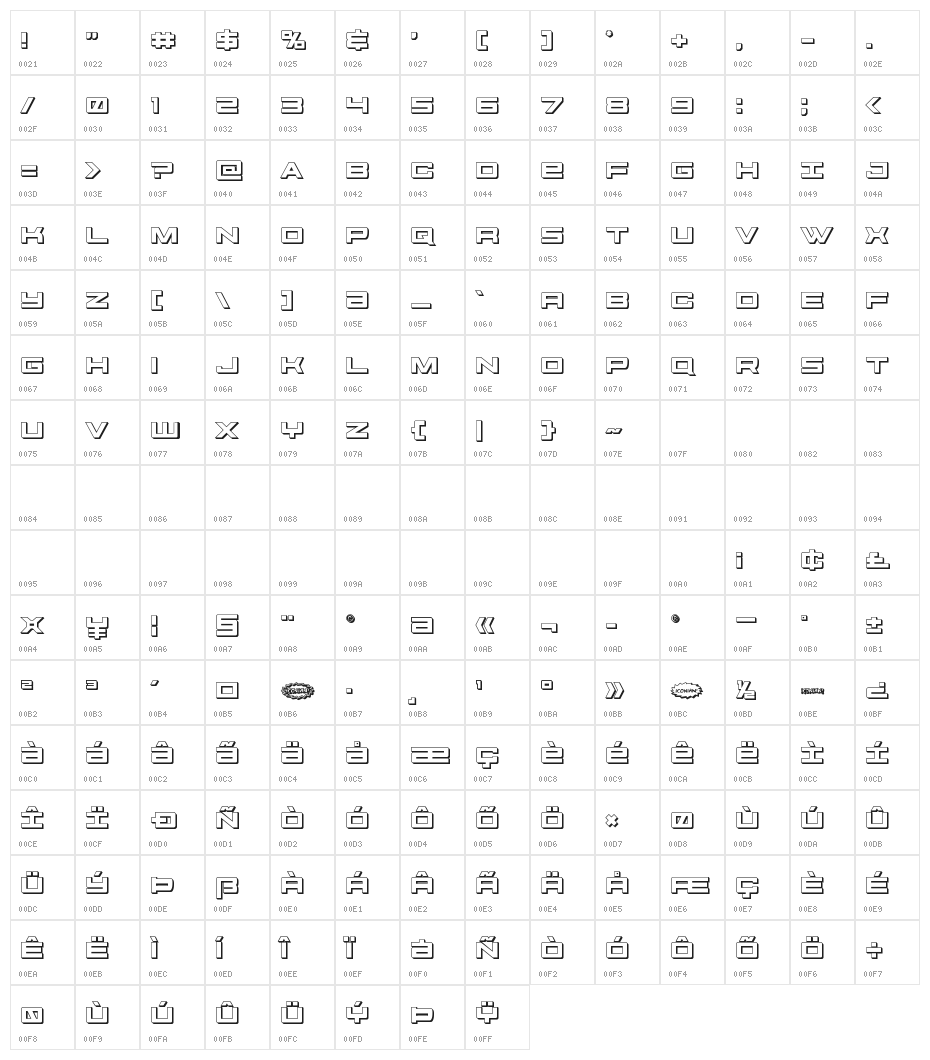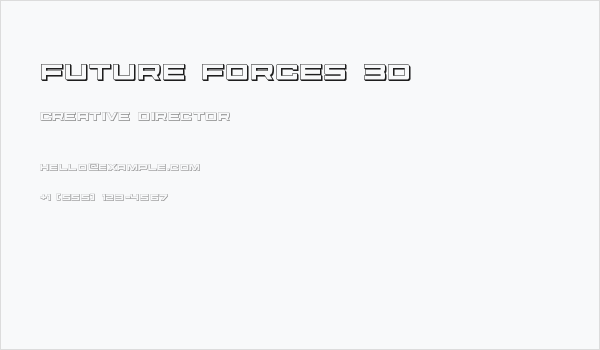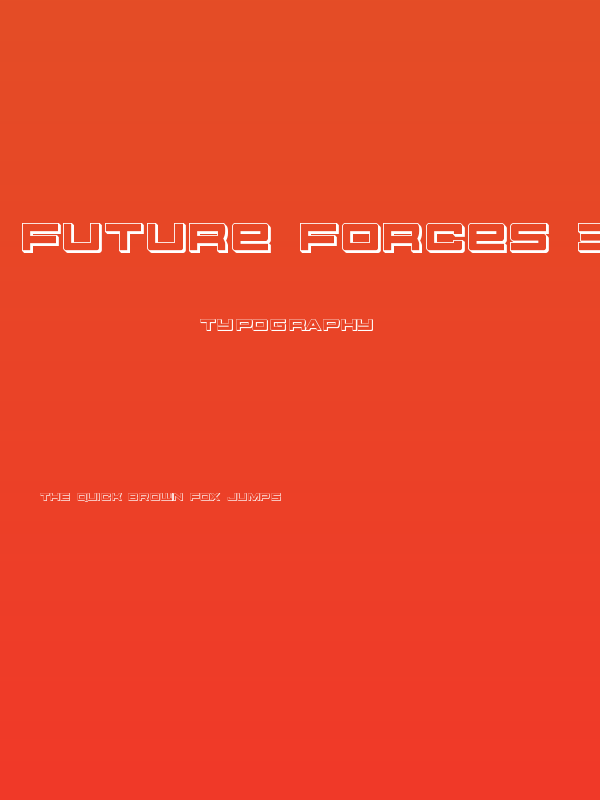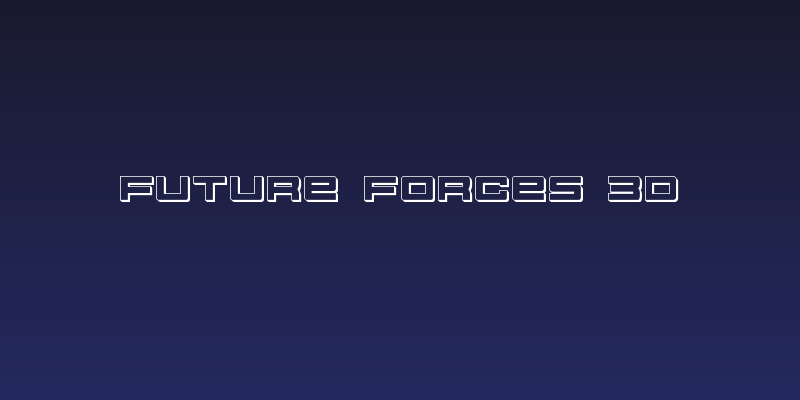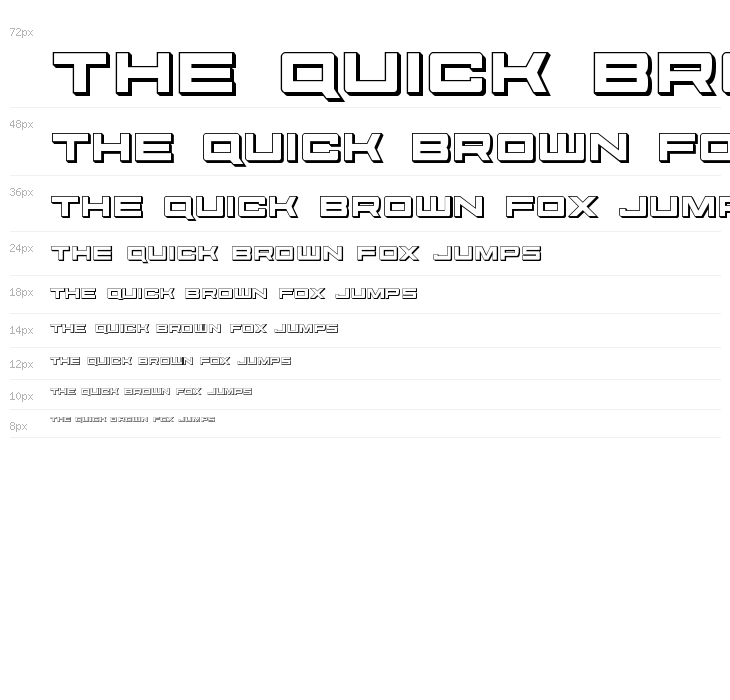
Future Forces 3D Font
✎ 3D
| Stile generale | Futuristic |
| Progetti proposti | Ideal for sci-fi themed designs, tech branding, video game titles, and futuristic posters. |